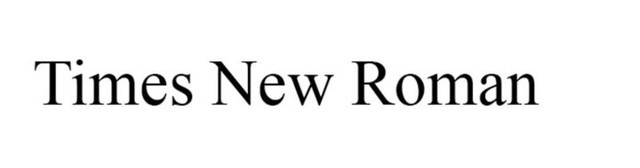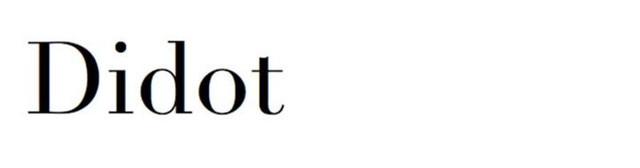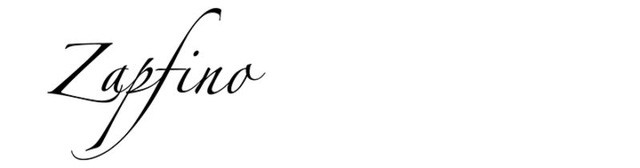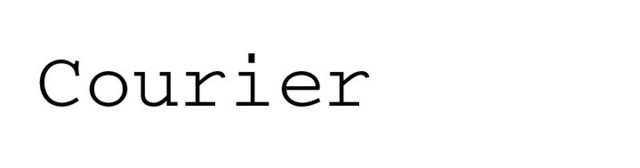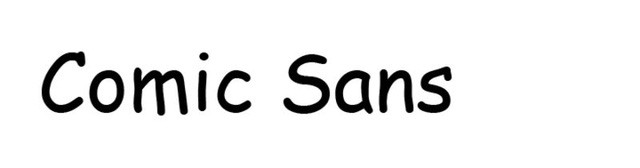
在简历中使用新罗马字体,例如“穿运动裤”来申请工作
编写简历时,您通常选择写哪种字体?如果您为简历选择时间新罗马字体,就像“穿运动服”进行工作面试。当我们编写文字时,我们大多数人都选择这种熟悉的字体,这并不是完全错误的,但不是最合适的字体供您放入CV以供工作。
简历(或简历)是工作面试的组成部分,不仅反映了您的学术背景和工作经验,而且还可以帮助雇主在编写简历时看到您自己的风格和创造力。但是,并非我们所有人都成功地通过简历表达了自己。许多犯了愚蠢错误的人,例如选择不适当的字体,使您在雇主面前失去了积分,而不知不觉。
长期以来,我们经常认为与设计或图形有关的工作需要关注在简历中选择字体。但是,这个概念是完全错误的!
因此,在当前使用的字体中,应该选择字体编写简历。请参考以下专家的评论!
1。helvetica字体
如果您想选择一种清晰,简单,不太挑剔并且不遵循趋势的字体,那么在编写简历时,Helvetica字体将是您的理想选择。当您使用此字体时,您会看起来更加成熟和正确。此外,如果您的简历包含许多不同的体验,活动,则使用这样的简单字体可以为您节省很多空间来“填补”所有令人印象深刻的成就。那里。这是一种非常安全的字体,也许这就是为什么它在业务上如此多的原因。
此外,您还有其他一些与Helvetica相似的选项,例如sans -serif字体 - 每个角色下的“脚”(如《时代》新罗马字体)都没有小的“脚”。
2。ProximaNova将是简历的绝佳选择
如果您想要具有许多优势(例如Helvetica)但“边缘”较少优势的字体,那么Proxima Nova字体也将是您简历的绝佳选择。这种字体给人带来柔和的感觉。虽然Helvetica看起来坚韧而严肃,但Proxima Nova又柔软,更圆。大多数雇主和客户都喜欢这种字体。但是,这不是免费的字体,因为美容通常花费很多,如果您想拥有此字体,则需要花费29.99美元才能在MyFonts上购买一种类型的字体。 COM和所有144种不同类型的$ 734。
3。如果您想定制读者,请选择Garamond字体
如果Helvetica既清晰又小,它将为您节省空间,而Proxima Nova太昂贵了,您仍然有一个选择:Garamond。如果您已经有很多经验,请使用此字体向有限的区域展示所有这些经验。根据专业设计师的说法,该字体可以很好地指导读者。你只需要那个,对吗?
4.泰晤士报新罗马通用字体
到目前为止,关于新罗马字体的流行时代仍然存在很多争议。因为有大量的设计师仍然认识到新罗马的时间是计算机上所有文档的常态。有些人认为新罗马字体看起来很麻烦,困惑,需要更换。但是,该字体太常见了,并且在整个历史上都使用了系统。但是,在许多情况下,它既正确又错误地使用了它。如果基于现在的新一代设计标准(清晰,简单,美丽),那么新罗马字体也许不等于上述字体。
5。DIDOT优质字体
如果您想要高级字体,Didot也不是一个坏建议。该字体使您的简历具有奢华和女性气质。据说对于那些与时装设计有关的工作的人来说,这是一个理想的选择。但是,在编写文档时,该字体不常见。
6。Zapfino将非常适合婚礼卡
对于Zapfino字体,您应该避免使用它,因为它太麻烦且精致,只有在制作婚礼卡时才适合使用。这是一种家庭字体,不在工作中使用,因为它很难阅读。
7。快递也是您在简历中绝对避免的字体
快递也是您绝对应该避免使用的字体。因为该字体有点像旧打字机的中风模拟。有时,正是古老的外观会给这个新时代的雇主带来负面印象。那些知道自己是谁的人呢?
8。漫画Sans对于简历申请人来说是非常糟糕的字体
漫画Sans是您工作简历的非常糟糕的字体。该字体仅适用于“青少年青少年”。如果您使用此字体制作简历,那肯定是一场灾难。更不用说,漫画无字体很大,因此您绝对应该避免为简历选择字体。
9。请在简历中添加一些最终表情符号
您是否曾经想过是否应该将表情符号插入简历中?专家的建议是肯定的,但最终将它们放在旁边或场外。 “有什么好主意可以帮助您打动雇主?”